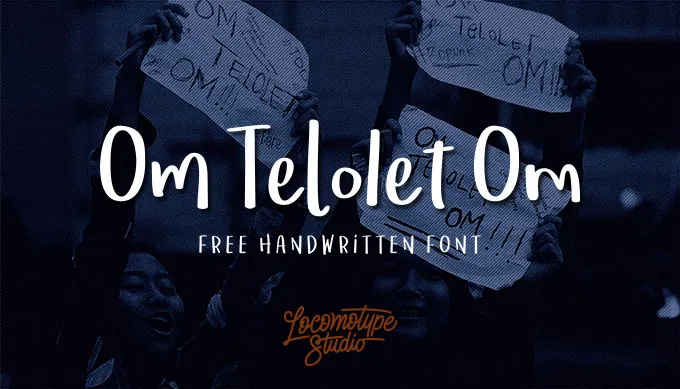
Om Telolet Om Font – Download Grátis
Esse é mais uma fonte escrita a mão que você pode baixar gratuitamente para seu próximo projeto de design. Através do designer Hamilton, chegamos ao Om Telolet Om Font, uma criação leve e fluida que se destaca entre as outras. Este font traz um estilo de escrita livre, com traços suaves e formas desviadas, proporcionando você um novo nível de flexibilidade em sua tipografia. Além disso, Om Telolet Om também inclui recursos OpenType como alternativas estilizadas e ligações básicas que permitem um design mais sofisticado e detalhado. Seja para criar títulos chamativos ou textos legíveis, essa fonte escrita a mão oferece uma variedade de opções. Para designers em busca de algo um pouco diferente e com alma, Om Telolet Om é definitivamente o caminho a seguir.